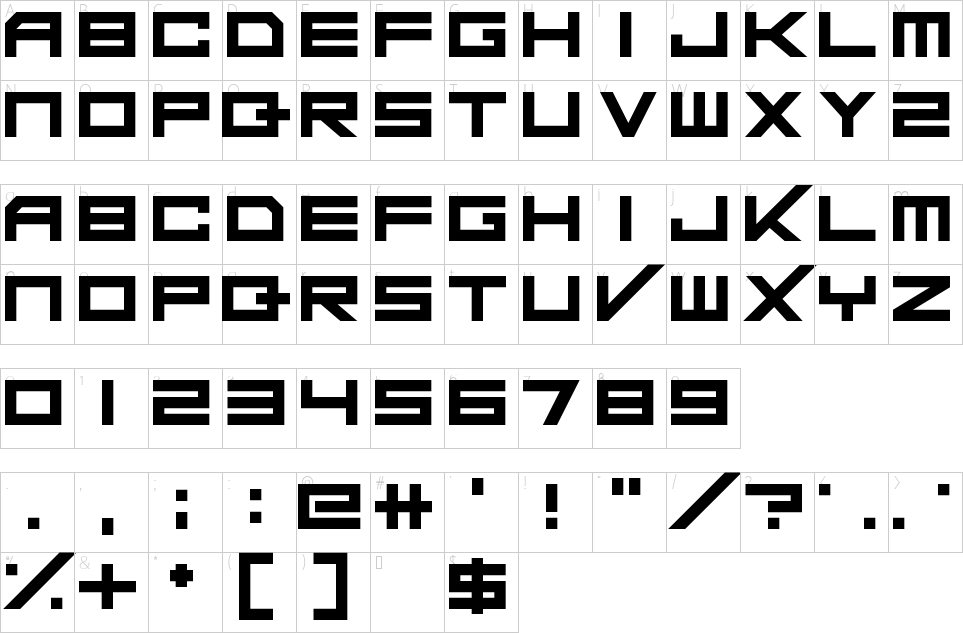
A fonte Da Mad Rave é uma escolha ideal para designers em busca de uma opção moderna e criativa para seus projetos. Desenvolvida pelo designer Darrell Flood, esta fonte apresenta um estilo vibrante e irreverente, que adorarão os criativos. Com uma download total de 7.277 vezes, é evidente que Da Mad Rave está ganhando a atenção e o respeito de profissionais de design. Seja para criar um design visual impactante ou estilizar textos de uma maneira única, Da Mad Rave traz a personalidade que tanto valorizamos em nossos trabalhos. Se você está procurando por uma fonte que não só enriqueça suas criações, mas também dá uma personalidade única para o seu trabalho, Da Mad Rave é um ótimo começo. Download Da Mad Rave para Windows e Mac hoje e destrave sua criatividade.